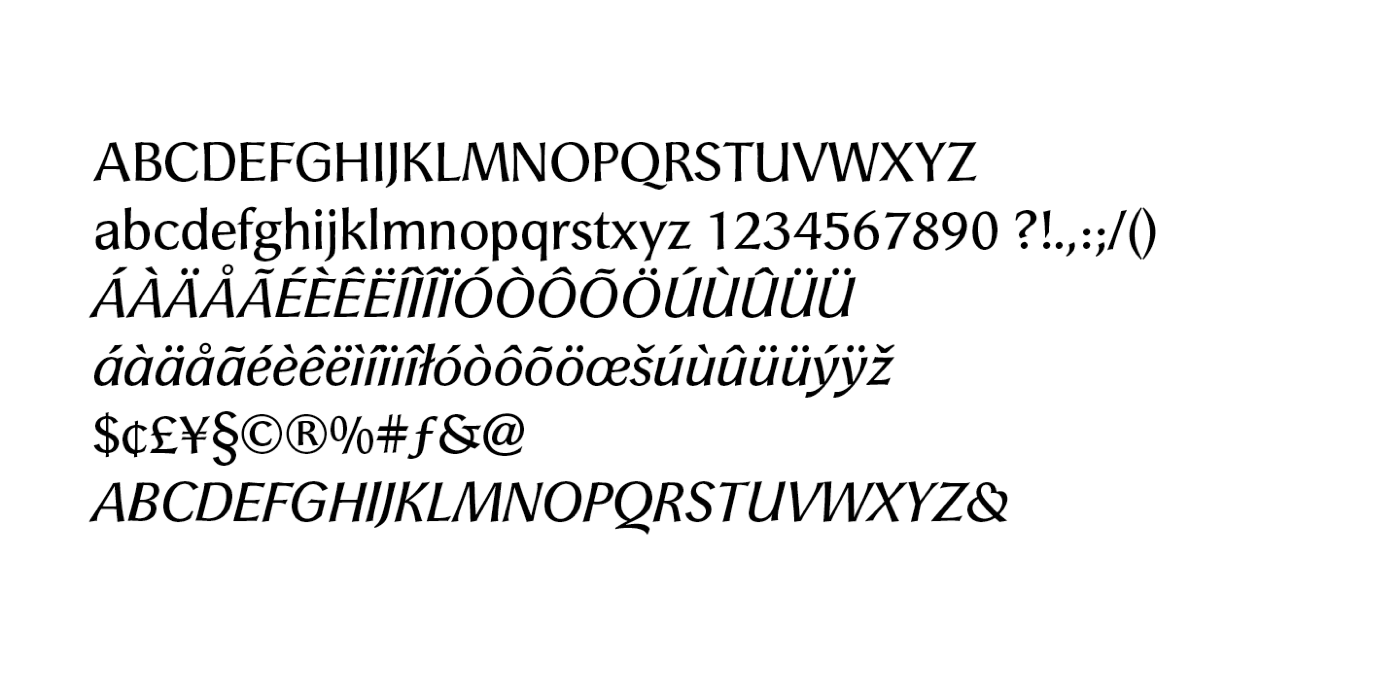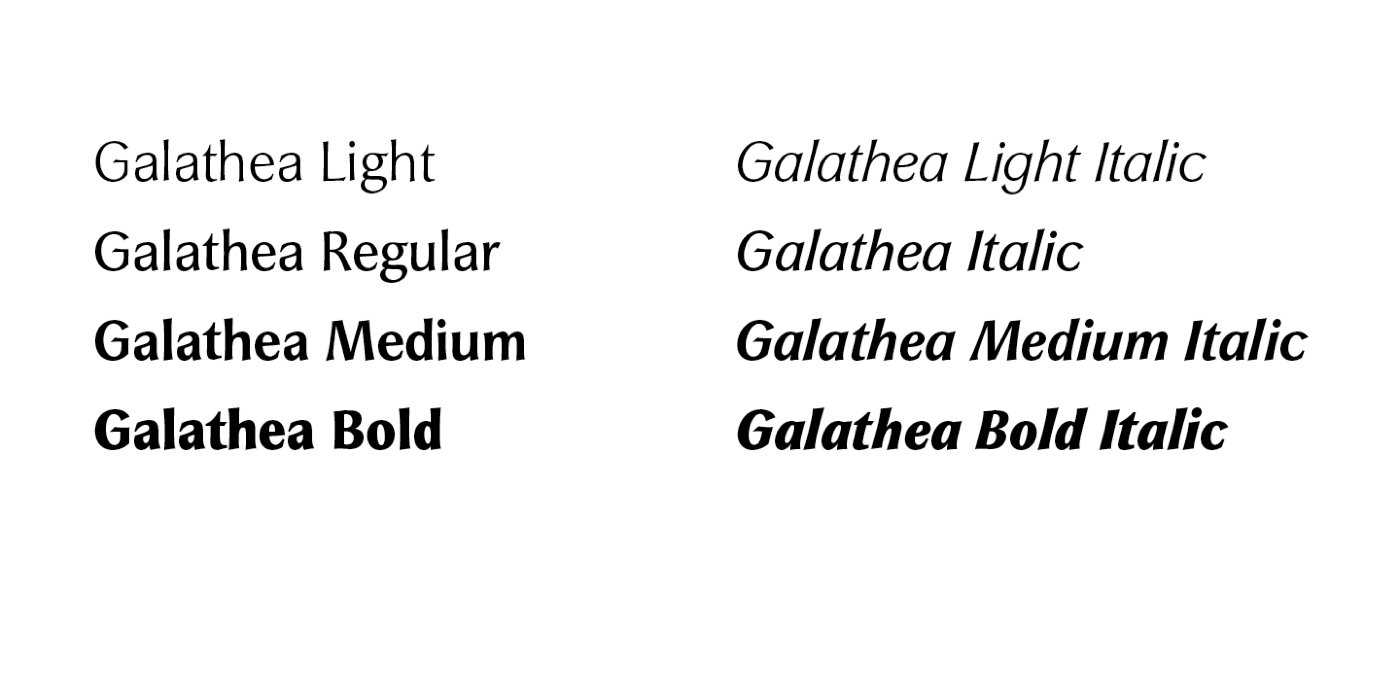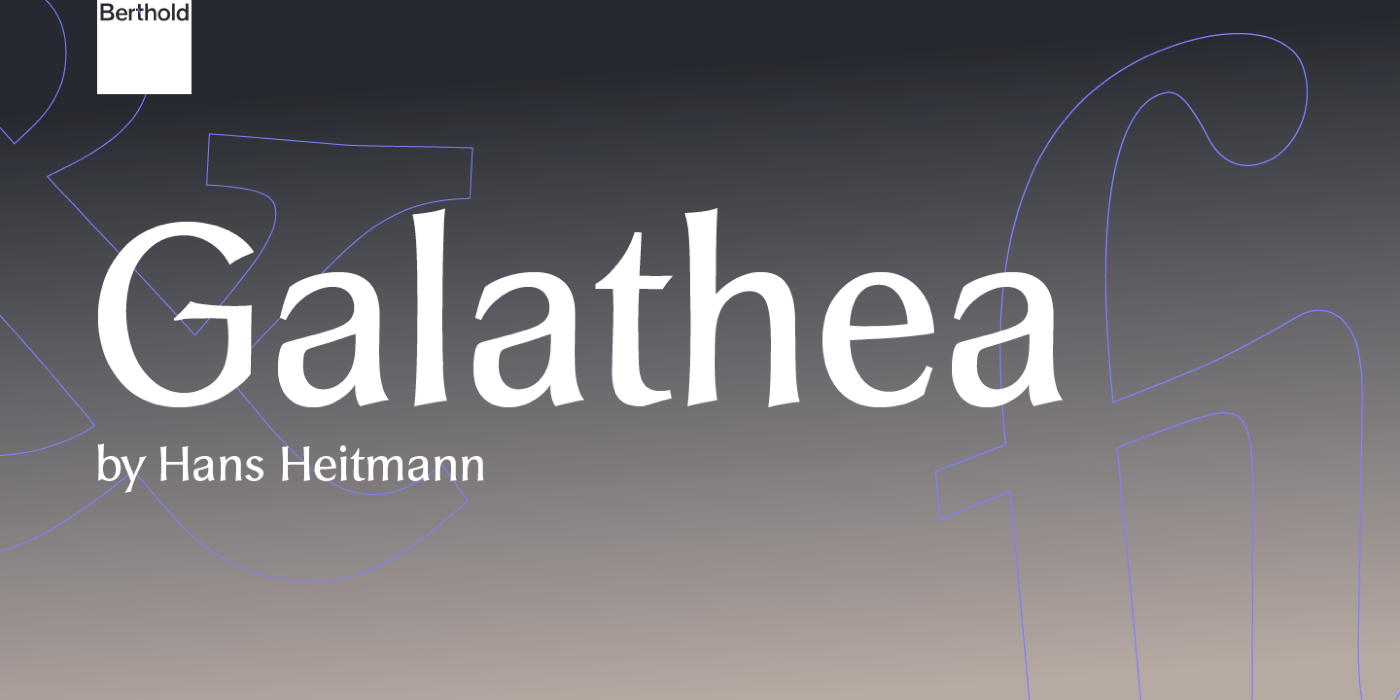
Die Galathea von Hans Heitmann stammt aus dem Jahr 1990. Die Schriftfamilie folgt dem Duktus einer Antiqua-Schrift, ohne jedoch tatsächlich Serifen zu besitzen. Die vier Strichstärken mit Kursiven besitzen eine westeuropäische Belegung und sind heute über Monotype verfügbar.